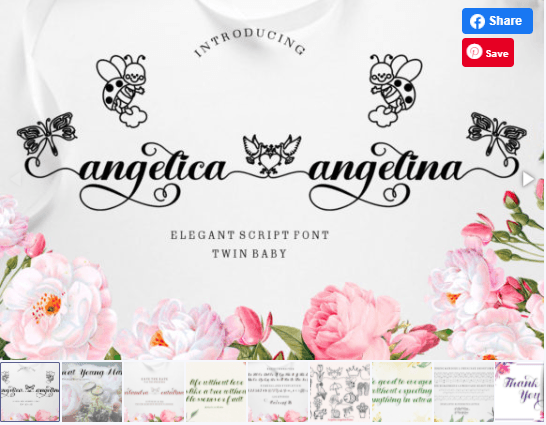
Angelica Angelina Font
Angelica Angelina - прекрасный шрифт с очаровательными игривыми персонажами, которые, кажется, танцуют вдоль базовой линии. Этот шрифт имеет кодировку PUA, что означает, что вы можете легко получить доступ ко всем глифам и росчеркам!